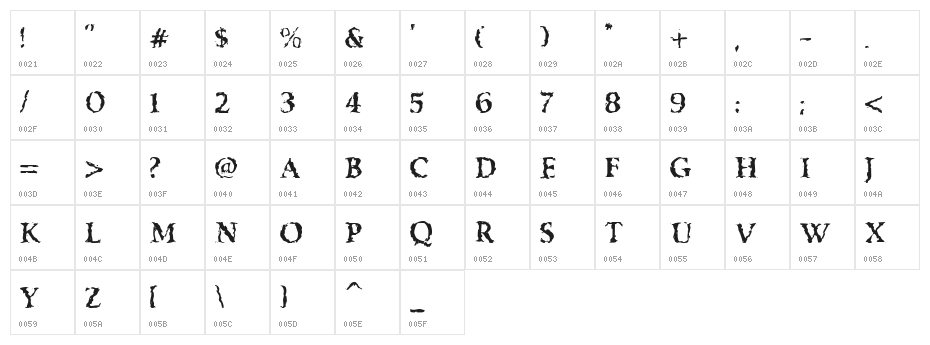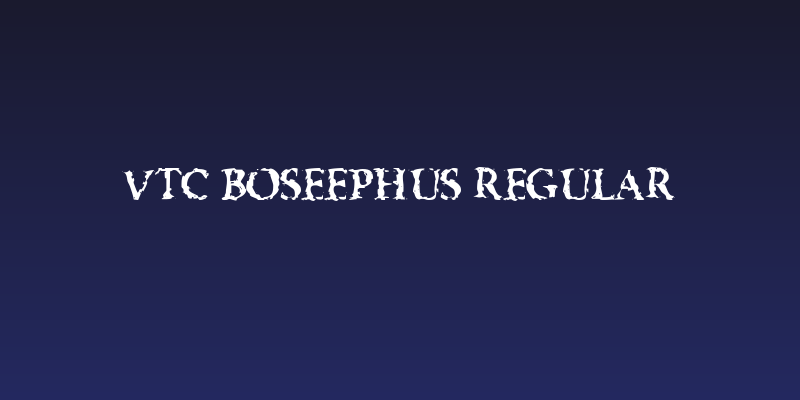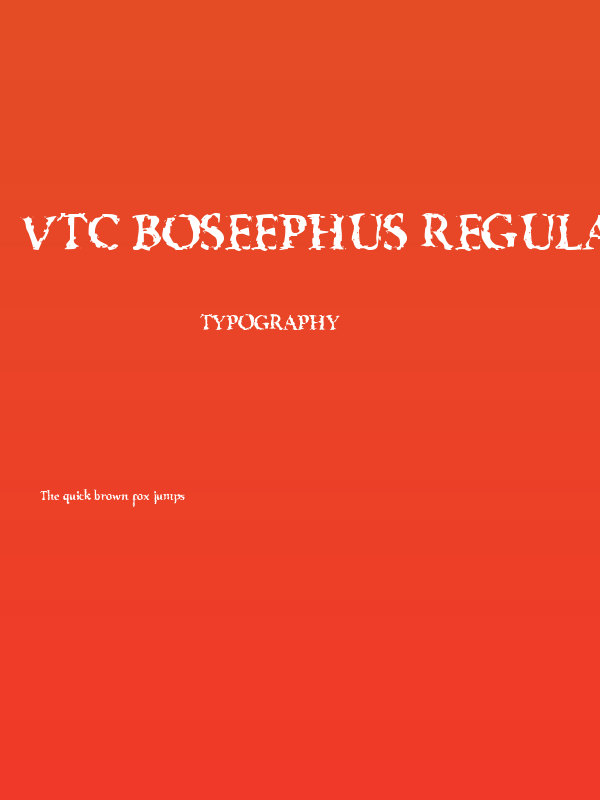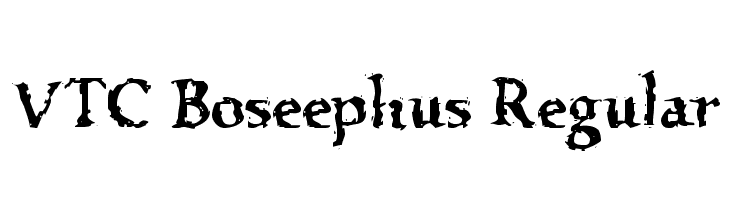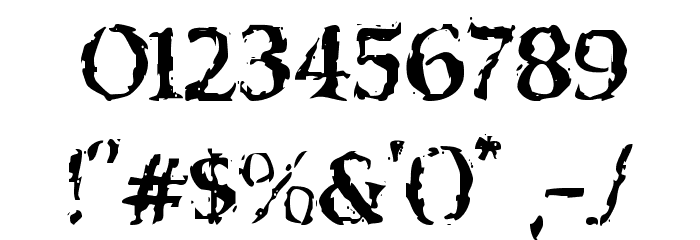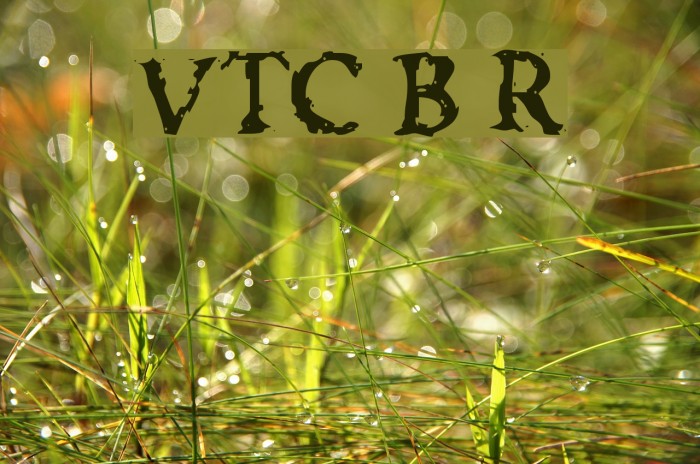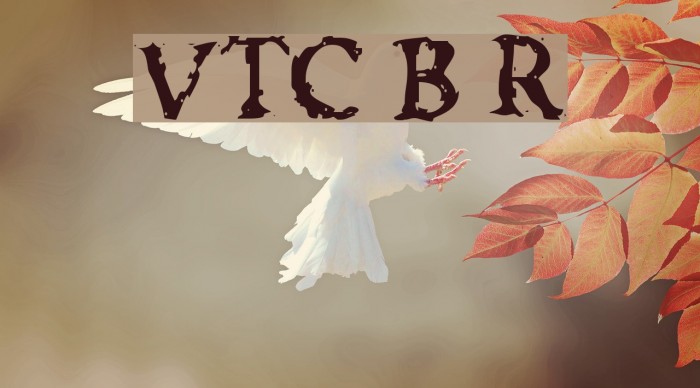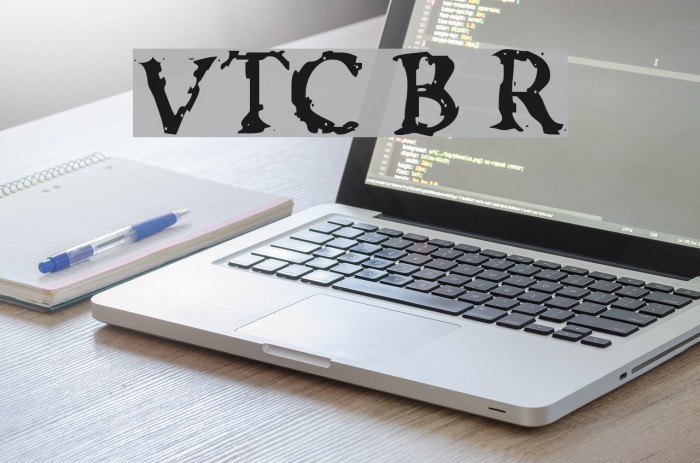
VTC Boseephus Regular Font
| Estilo geral | Vintage, Grunge |
| Projetos propostos | Ideal for album covers, posters, branding for alternative or rock music events, and any project requiring a bold, edgy statement. |